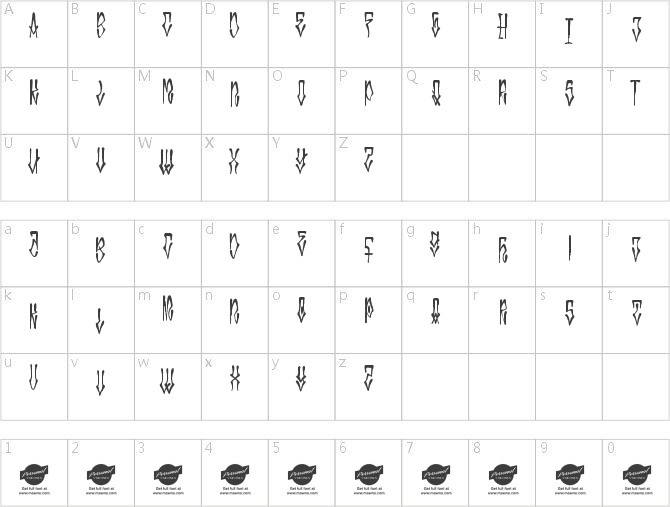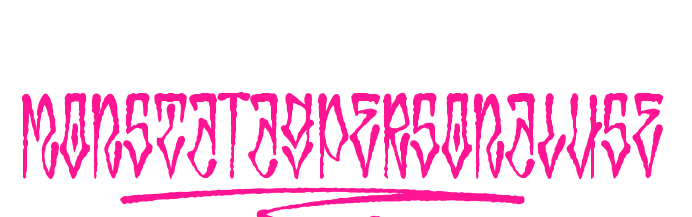
MonstaTag_PersonalUse 詳情頁(yè)
MonstaTag_PersonalUse字體字庫(kù)是一款讓人賞心悅目、百看不厭的英文字體,適合各類廣告和產(chǎn)品包裝設(shè)計(jì)應(yīng)用,字體大小0.48MB,格式為ttf字體,上傳用戶是小籃子,作者/版權(quán)方為未知